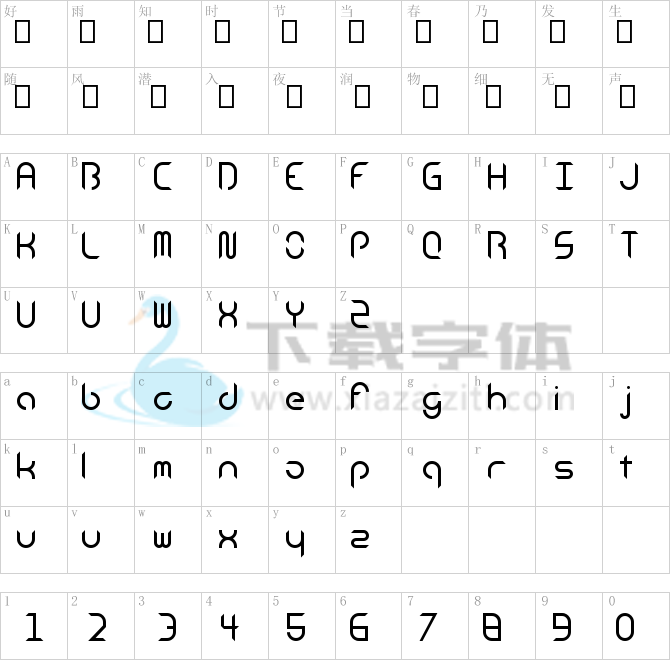
Android Insomnia.ttf字体下载,这款字体结构工整、笔画清晰,兼顾美观与易读性,适用于标题、正文、海报、包装、LOGO 等多种场景。字形优雅稳定,风格百搭耐看,适配日常排版与创意设计,让文字呈现更舒适、更具质感。Android Insomnia.ttf字体下载一笔一画,皆是细节,以均衡的比例、流畅的线条打造舒适视觉体验,字形端正大气,风格简约现代。无论是商业设计、品牌宣传还是日常排版,都能轻松驾驭,让文字更有格调与力量。Android Insomnia.ttf字体下载字体下载。